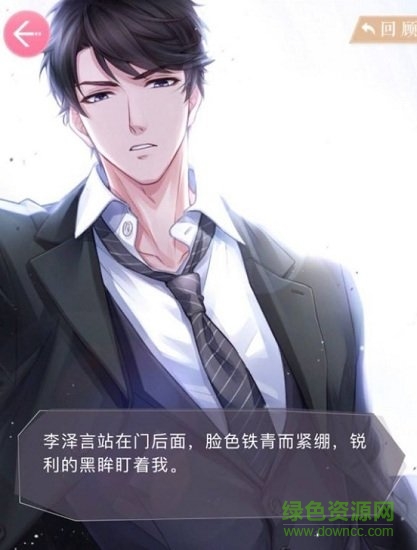
漢儀澤言體是人氣戀愛(ài)游戲《戀與制作人》中男主李澤言的專屬字體,自己深沉而霸道,就如李懟懟同學(xué)的性格,簡(jiǎn)直不要太蘇,喜歡的朋友就來(lái)綠色資源網(wǎng)下載吧!
出自于人氣手游,但漢儀字庫(kù)并未發(fā)行本款字體,而截圖上的文字經(jīng)過(guò)對(duì)比,顯示為:方正清刻本悅宋簡(jiǎn)體,干凈精簡(jiǎn),造型對(duì)稱而統(tǒng)一,使用較為廣泛。